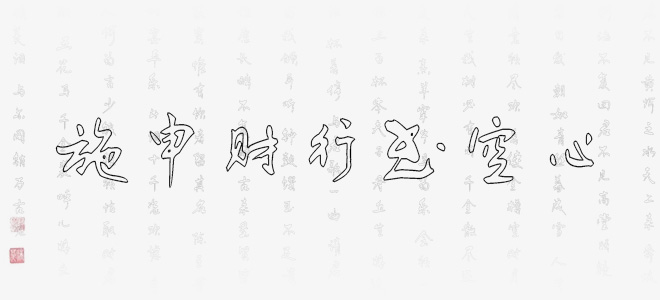
施申財(cái)行書空心是一款賞心悅目的空心行書字體,字體線條粗細(xì)適中,筆畫隨性,結(jié)構(gòu)灑脫自在,具有很好的視覺感,適合于文化類的宣傳設(shè)計(jì)、商業(yè)類品牌的廣告和產(chǎn)品包裝設(shè)計(jì)以及個(gè)性化文字排版等較多場景。
施申財(cái)行書空心